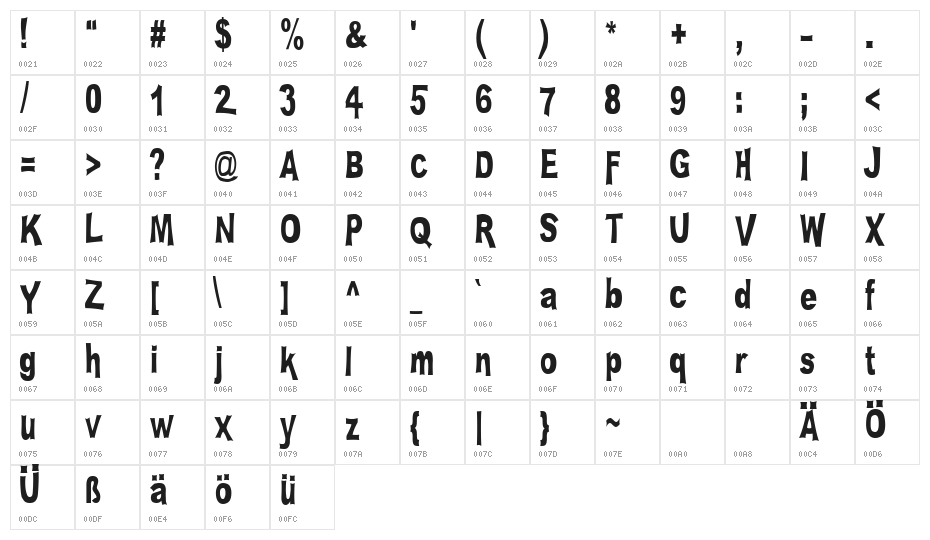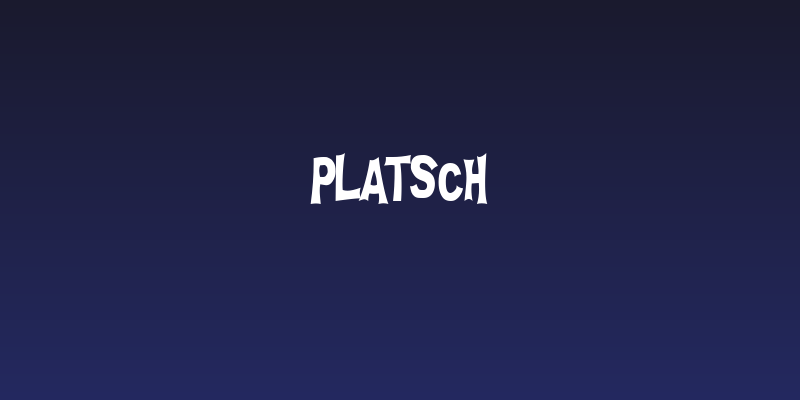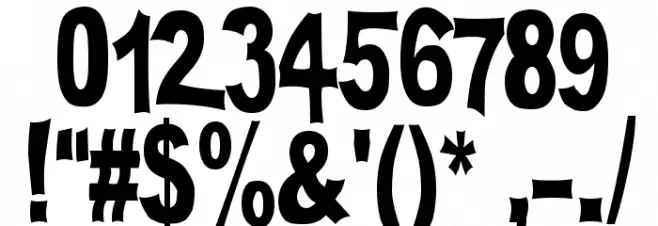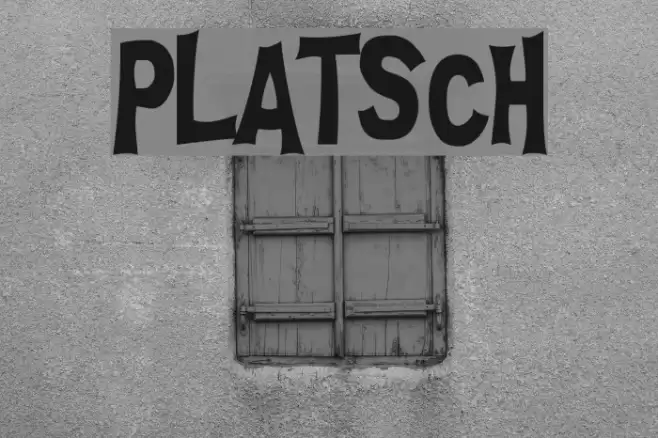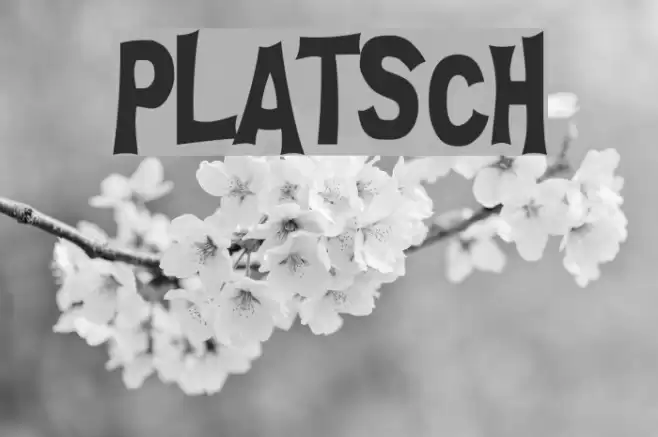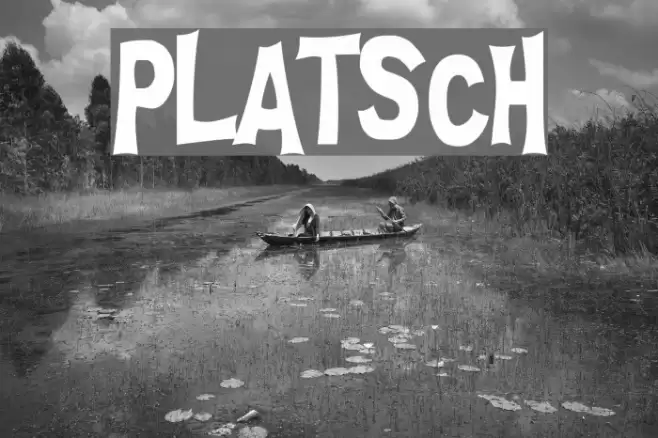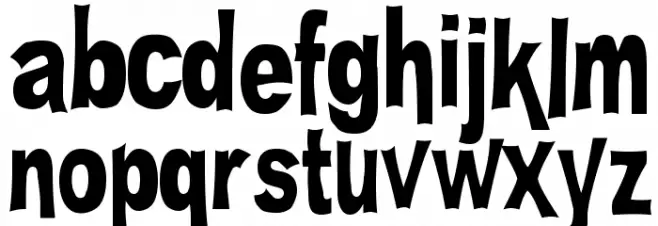
PLATSCH Font
✎ Comic
| カテゴリ | Comic |
| 全体的なスタイル | Playful, Whimsical, Hand-drawn |
| 用途 | Headlines, Posters, Branding |
| おすすめプロジェクト | Ideal for children's books, playful branding, posters, and creative projects that require a fun and engaging typeface. |